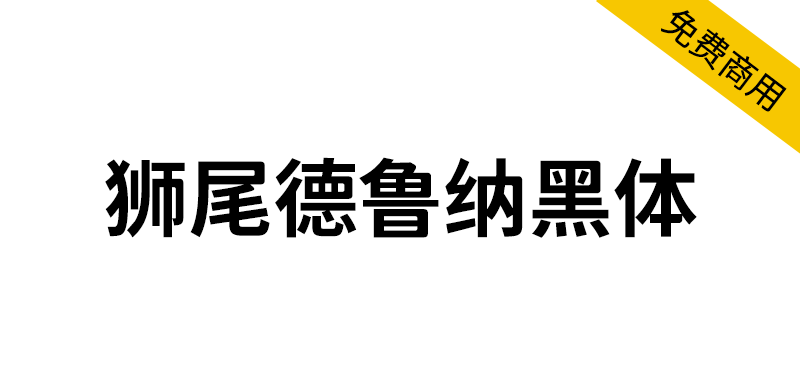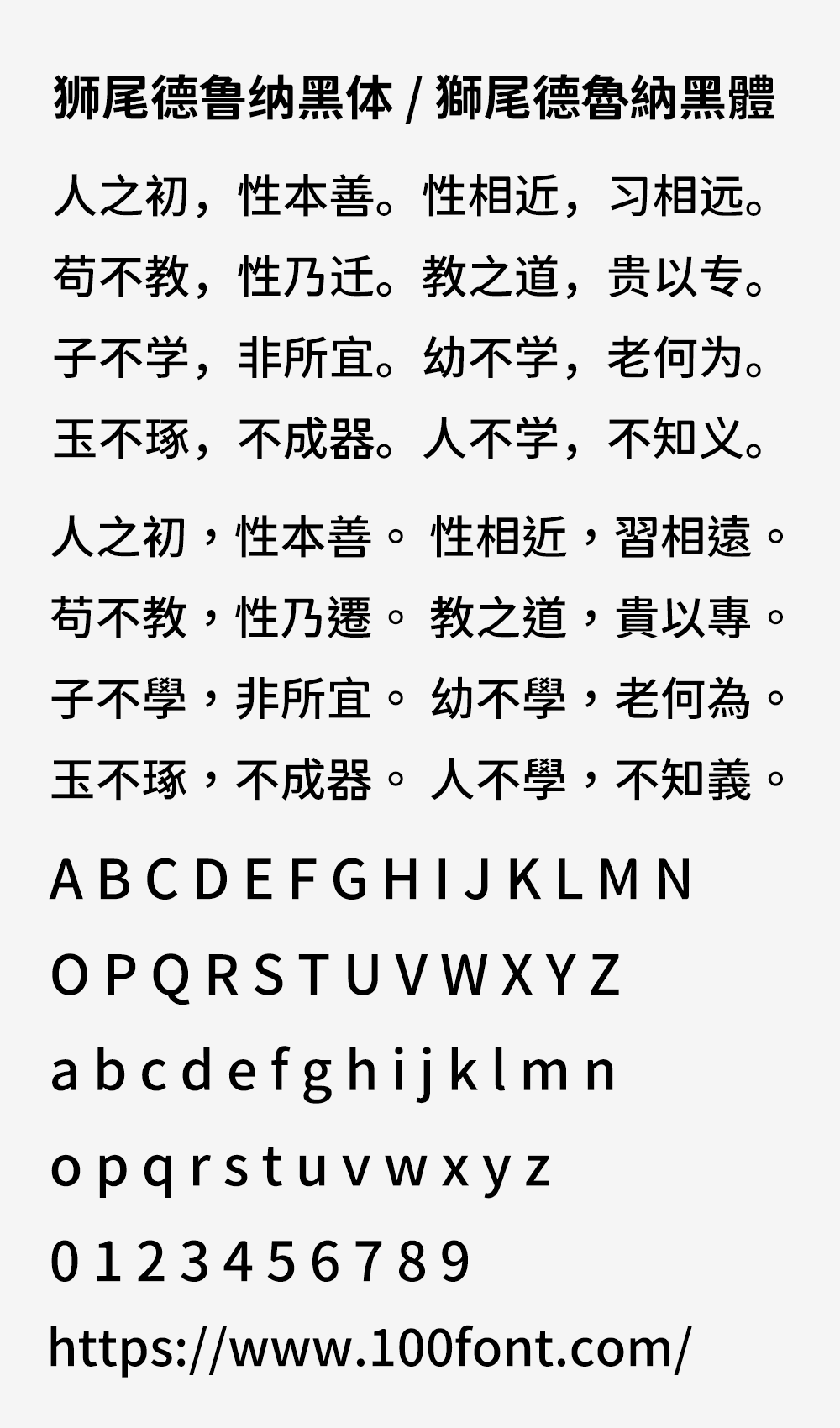
狮尾德鲁纳黑体基于思源黑体的右侧变圆和拔脚改造,更加简明现代化的字体。和思源黑体一样,有7种字重,支持简体中文、繁体中文、韩文与日文,可以免费商用,欢迎大家自由应用、自由优化、自由改作!
狮尾德鲁纳黑体与「狮尾D露西」差别在笔触是否有做调整,狮尾德鲁纳黑体所套用的效果较少,在笔触没有做调整。
狮尾德鲁纳黑体与「狮尾D卤腿黑体」差别在有没有拔脚,「拔脚」就是会有较少的笔画,例如移除「口」字的左右下角会多出的短线条。有拔脚的字会较圆,但是会造成有些字因直接去掉腿后左右不平衡、左右不对衬的「悬空」问题。改使用「腿」系列字体就不会有这个问题。